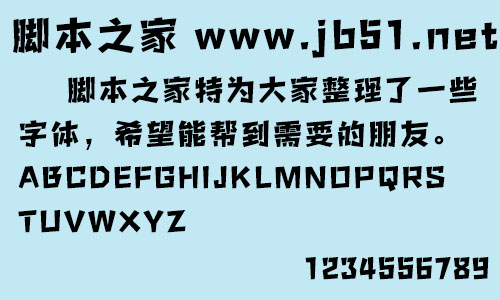
方正快活體簡Heavy是由方正字庫最新開發(fā)的一款中文字體,這款字體的靈感來源于換牙時(shí)期缺少牙齒的孩童。字體排版整齊,一眼看上去有種給人一種搞笑的感覺,具有強(qiáng)烈的視覺影響力,適合應(yīng)用于藝術(shù)設(shè)計(jì)、平面宣傳設(shè)計(jì)、網(wǎng)頁設(shè)計(jì)等領(lǐng)域,需要的朋友可以前來本站下載。